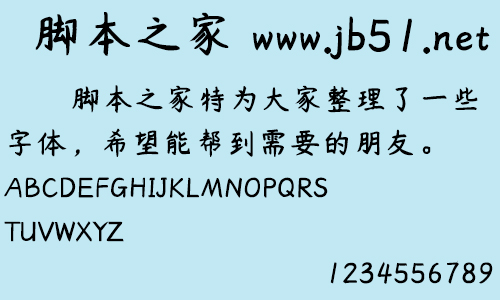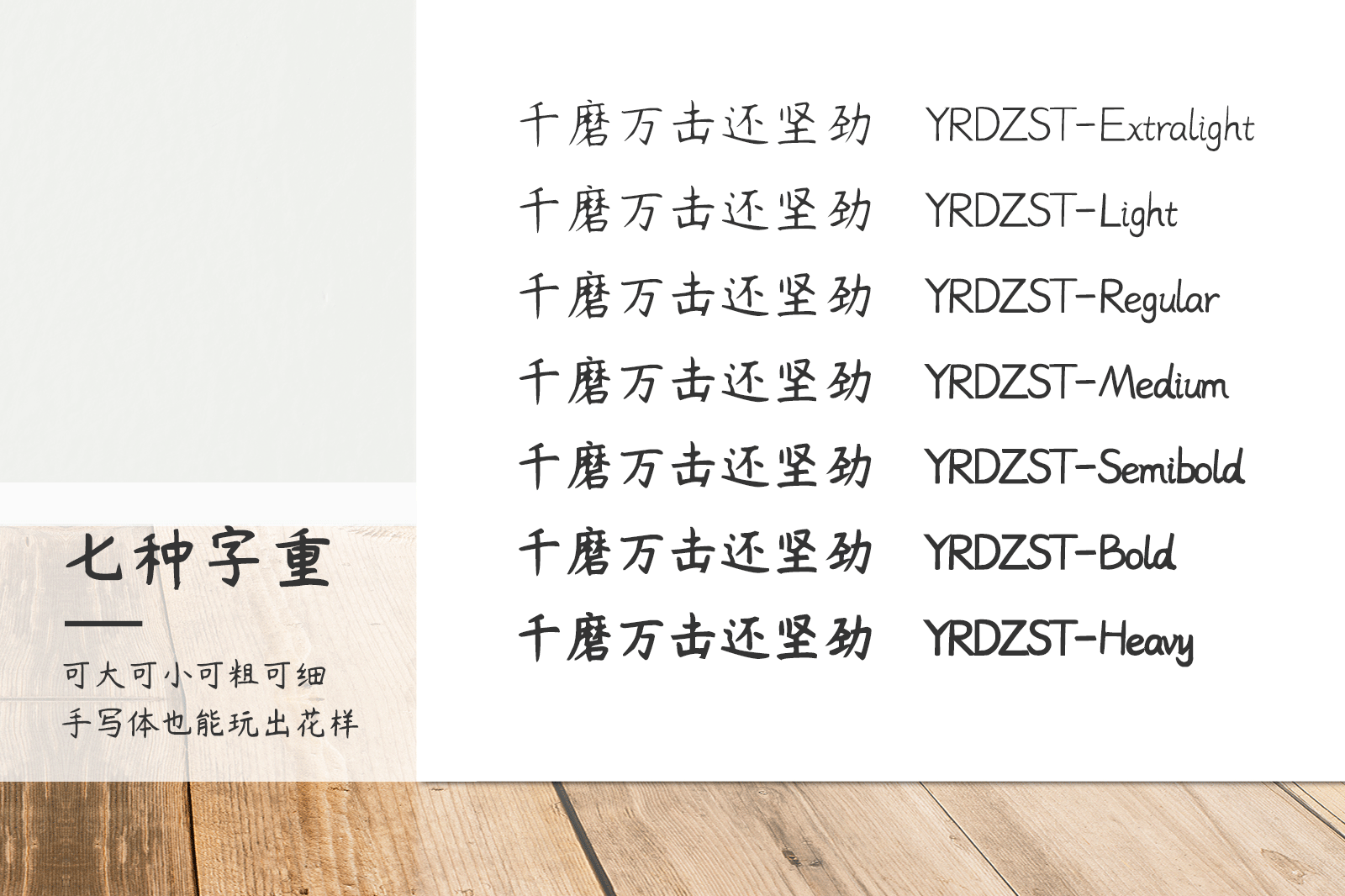
楊任東竹石體是一款可商用的手寫字體,字體整體簡潔明了,大方,支持中文簡體、英文字母、數(shù)字符號等格式,適合應(yīng)用與藝術(shù)設(shè)計、平面宣傳設(shè)計、網(wǎng)頁設(shè)計、書籍印刷等領(lǐng)域,需要的朋友可以前來本站下載。
楊任東竹石體于2017年4月26日世界知識產(chǎn)權(quán)日正式發(fā)布,本字體版本為1.23。
字體按照GB2312-80書寫,并增補(bǔ)了少量常見漢字;整套字體有7個字重,共計50000余個字符
本套字體的部分文字還存在重心不一致、細(xì)節(jié)瑕疵等問題,不過作為手寫體并不影響使用,作者將在后續(xù)版本中不斷改進(jìn)。
字體更新說明
楊任東竹石體1.23為正式發(fā)布版本,字體將持續(xù)更新,更新內(nèi)容包括:
字符的增補(bǔ)
生僻字、繁體字、外文、符號等;
字型修正
部分文字存在重心不一致、細(xì)節(jié)瑕疵等問題,目前不影響使用,將在之后的版本中不斷改進(jìn);